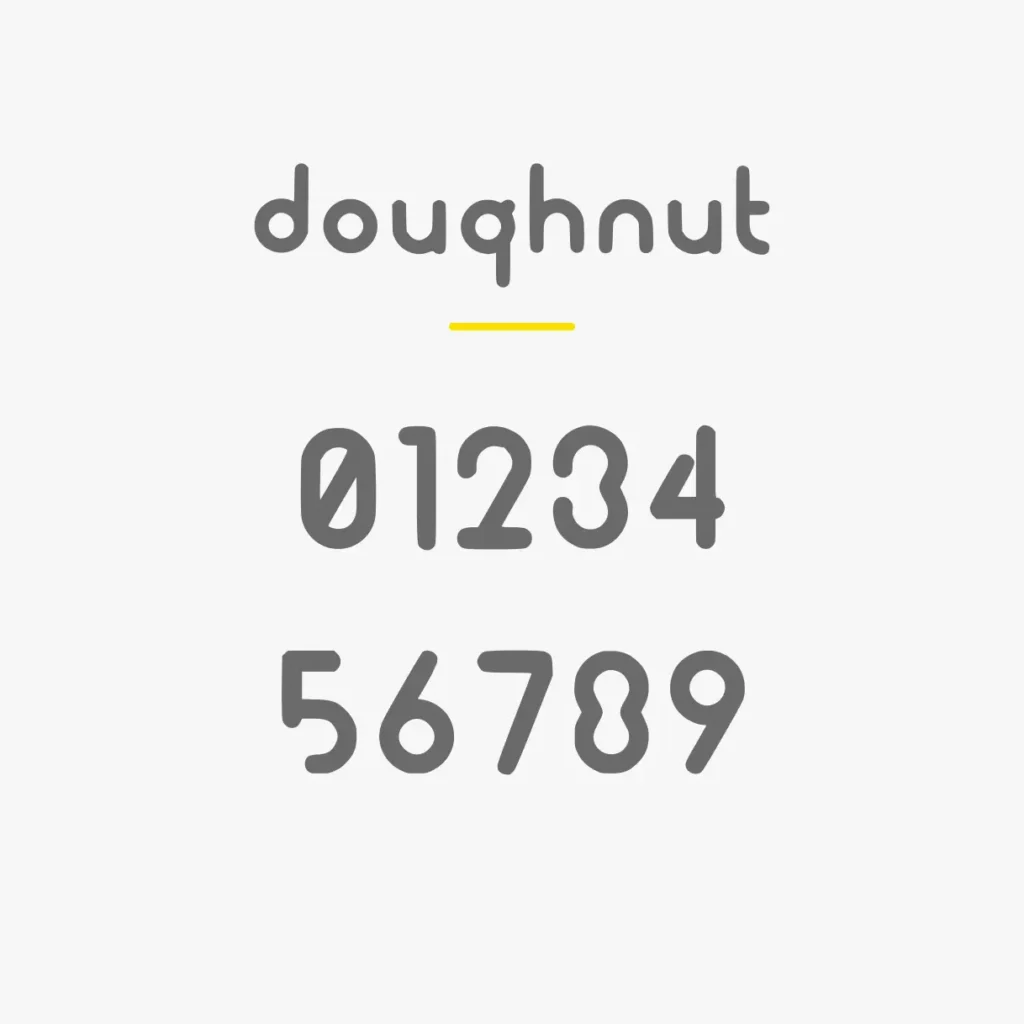
数字フォントは、ロゴやポスター、SNS画像、動画サムネイル、資料制作など幅広いシーンで活躍します。同じ数字でもフォントによって印象は大きく変わり、おしゃれな雰囲気を演出したり、かわいらしさや力強さを表現したりできます。
この記事では、おしゃれ・かわいい・かっこいい・太字で目立つ・レトロ・デジタル風など、用途やデザインテイスト別におすすめの数字フォントを紹介します。無料で使えるフォントや商用利用できるフォントも掲載しているので、数字デザインにこだわりたい方はぜひ参考にしてください。
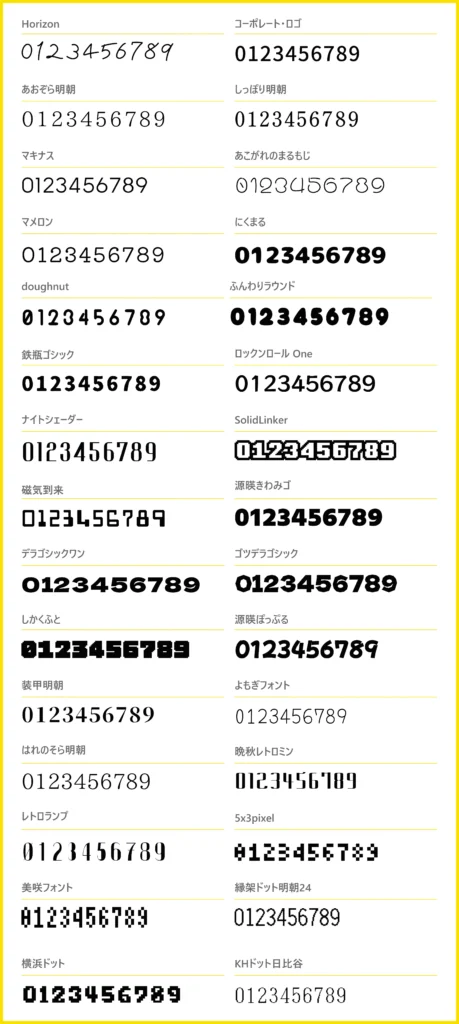
数字フォントを選ぶポイント
数字フォントを選ぶ際は、デザイン性だけでなく視認性や利用用途も重要です。数字は価格表示やランキング、背番号、時計表示など情報を伝える役割が強いため、用途に適したフォントを選ぶことで見やすさや訴求力が向上します。
用途に合わせて数字フォントを選ぶ
数字フォントには、ロゴ向け・ポスター向け・スポーツ向け・デジタル表示向けなどさまざまな種類があります。まずは使用目的を明確にし、デザインとの相性を確認しながら選びましょう。
数字の見やすさを確認する
数字フォントによっては「1」と「7」、「0」と「O」などが似て見える場合があります。資料や価格表など正確な情報伝達が必要な場面では、判別しやすい数字デザインを選ぶことが大切です。
日本語フォントとの相性も重要
数字だけが目立ちすぎると全体のデザインバランスが崩れることがあります。本文や見出しで使用する日本語フォントとの組み合わせも意識すると、統一感のあるデザインに仕上がります。
おしゃれな数字フォントおすすめ
洗練された数字デザインは、ロゴやブランドサイト、価格表示などに適しています。シンプルながらも存在感のある数字フォントを選ぶことで、デザイン全体を上品に見せることができます。
Horizon
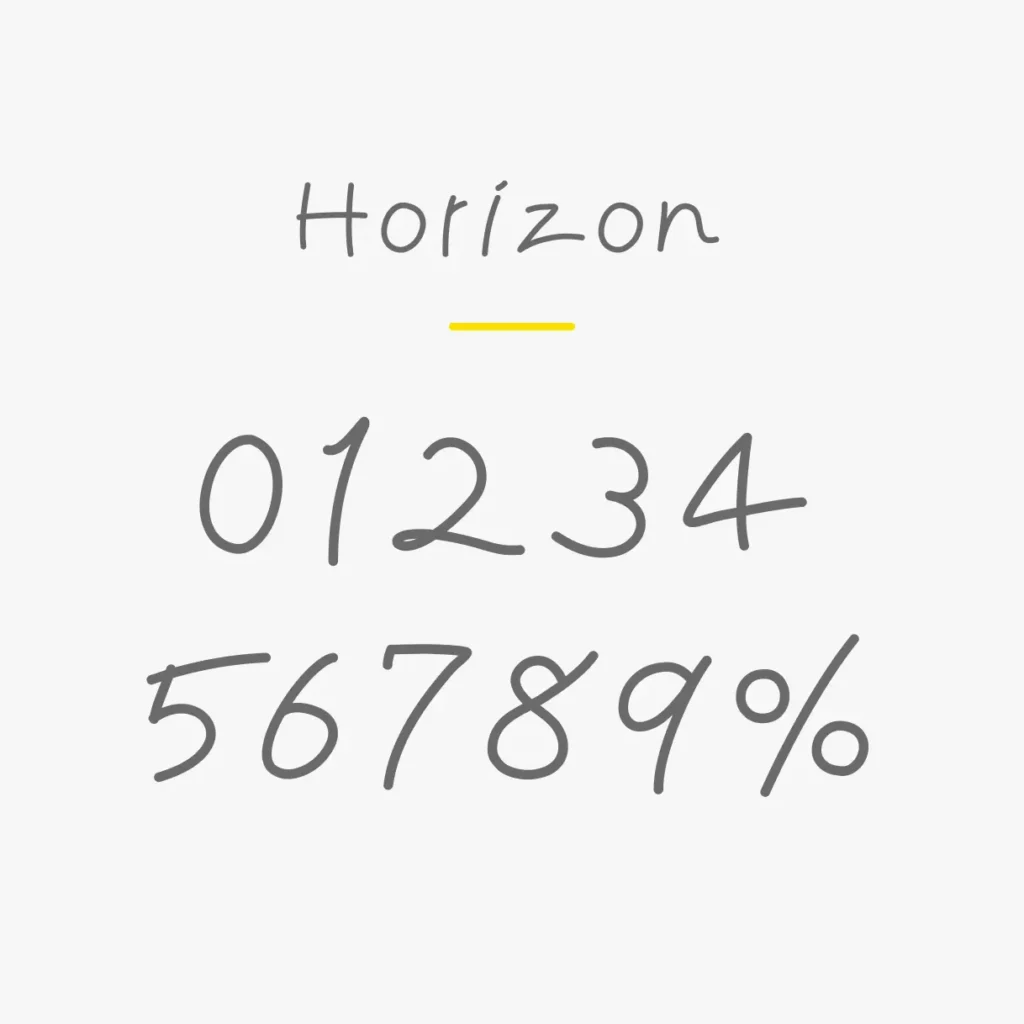
| ジャンル | おしゃれ・近未来 |
| 数字の雰囲気 | シャープ・未来的 |
| おすすめ用途 | ロゴ・サムネイル・ポスター |
| 相性のいいデザイン | テクノロジー・SF・ミニマル |
近未来的でスタイリッシュなデザインが特徴のフォントです。直線的な数字デザインが印象的で、テクノロジー系やファッション系のデザインに向いています。
コーポレート・ロゴ
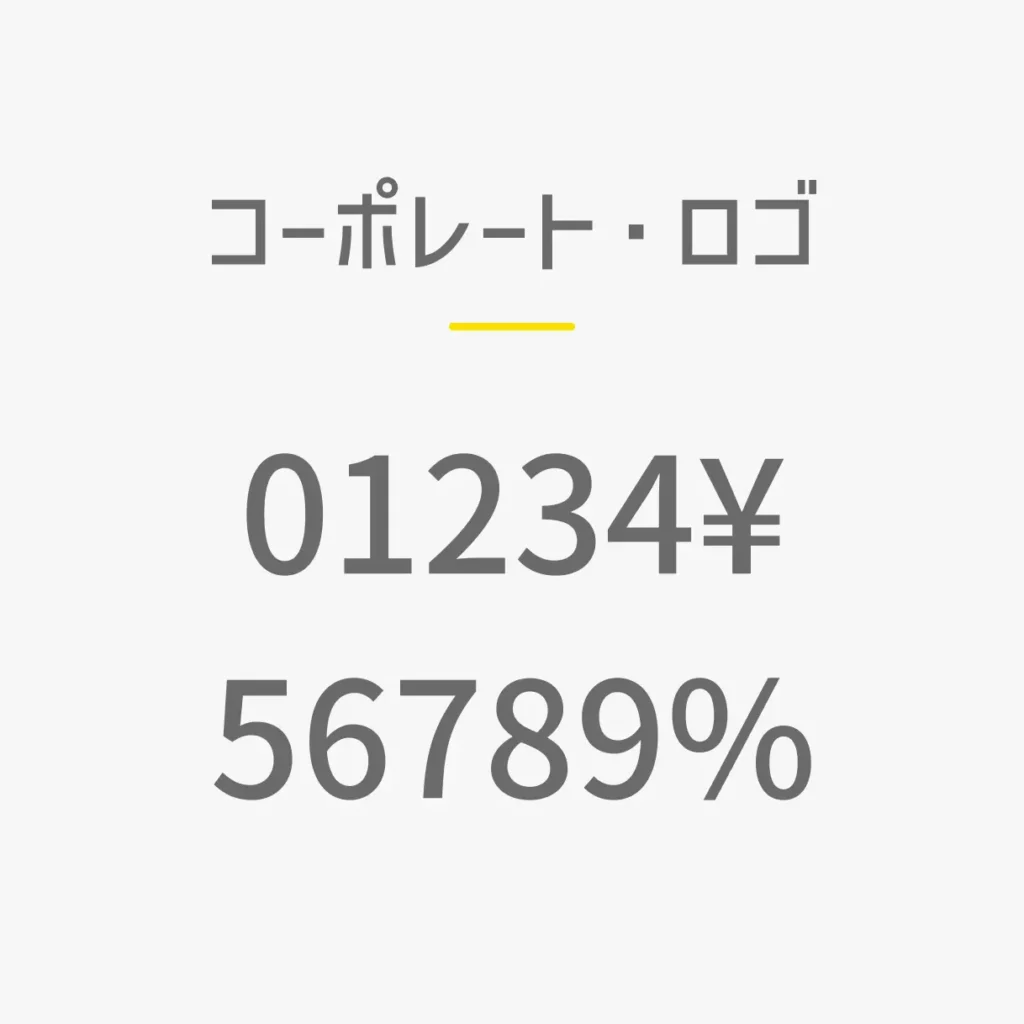
| ジャンル | シンプル・モダン |
| 数字の雰囲気 | すっきり・読みやすい |
| 相性のいいデザイン | ミニマル・コーポレート |
視認性とデザイン性を兼ね備えた人気フォントです。数字も美しく整っており、ロゴ制作やWebデザイン、資料作成など幅広い用途で活用できます。
あおぞら明朝
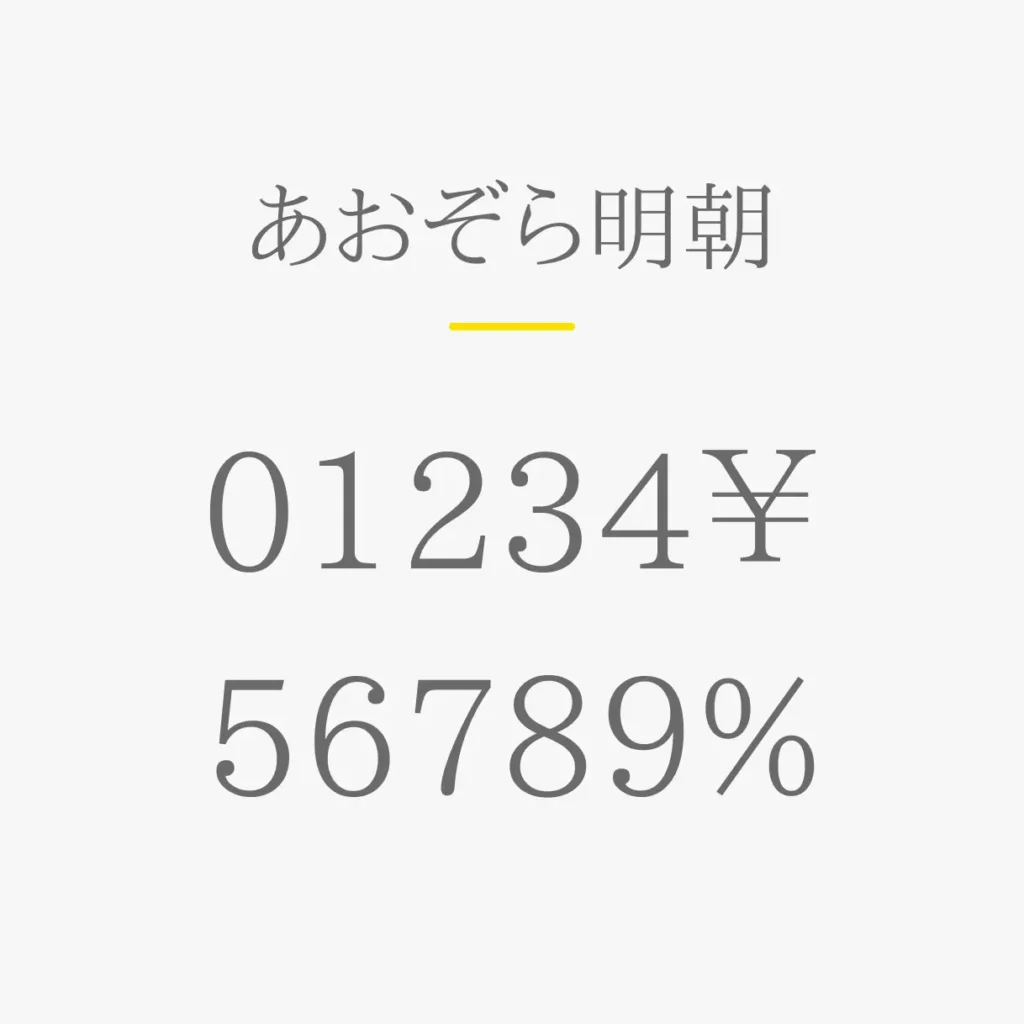
| ジャンル | おしゃれ・明朝体 |
| 数字の雰囲気 | 上品・繊細 |
| 相性のいいデザイン | 和モダン・ナチュラル |
上品で落ち着いた雰囲気を持つ明朝体フォントです。数字にも繊細な印象があり、高級感のあるデザインや和モダンな表現に適しています。
しっぽり明朝
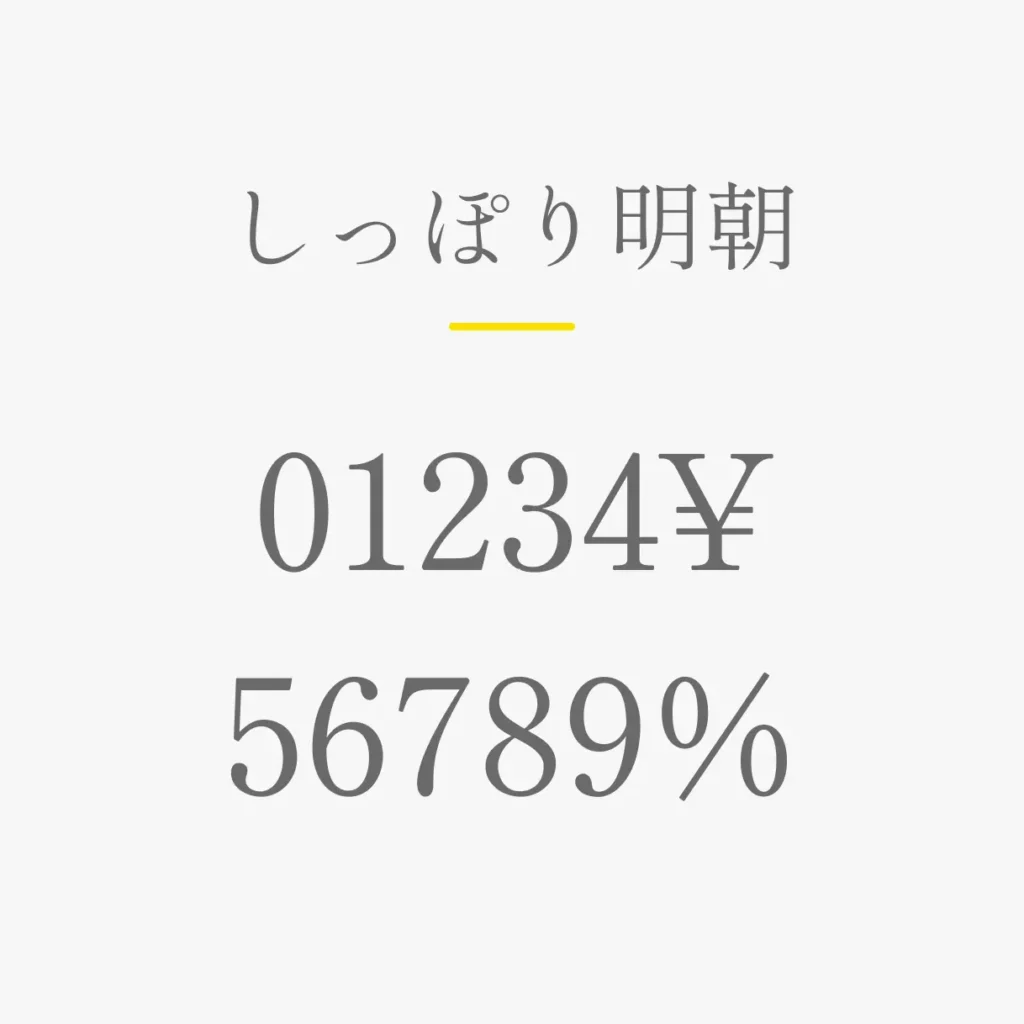
| ジャンル | 和モダン |
| 数字の雰囲気 | 上品・やわらかい |
| 相性のいいデザイン | 韓国風・和モダン |
和モダンな雰囲気を持つ明朝体フォントです。数字にも品のある印象があり、美容系やブライダル関連のデザインにも人気があります。
マキナス
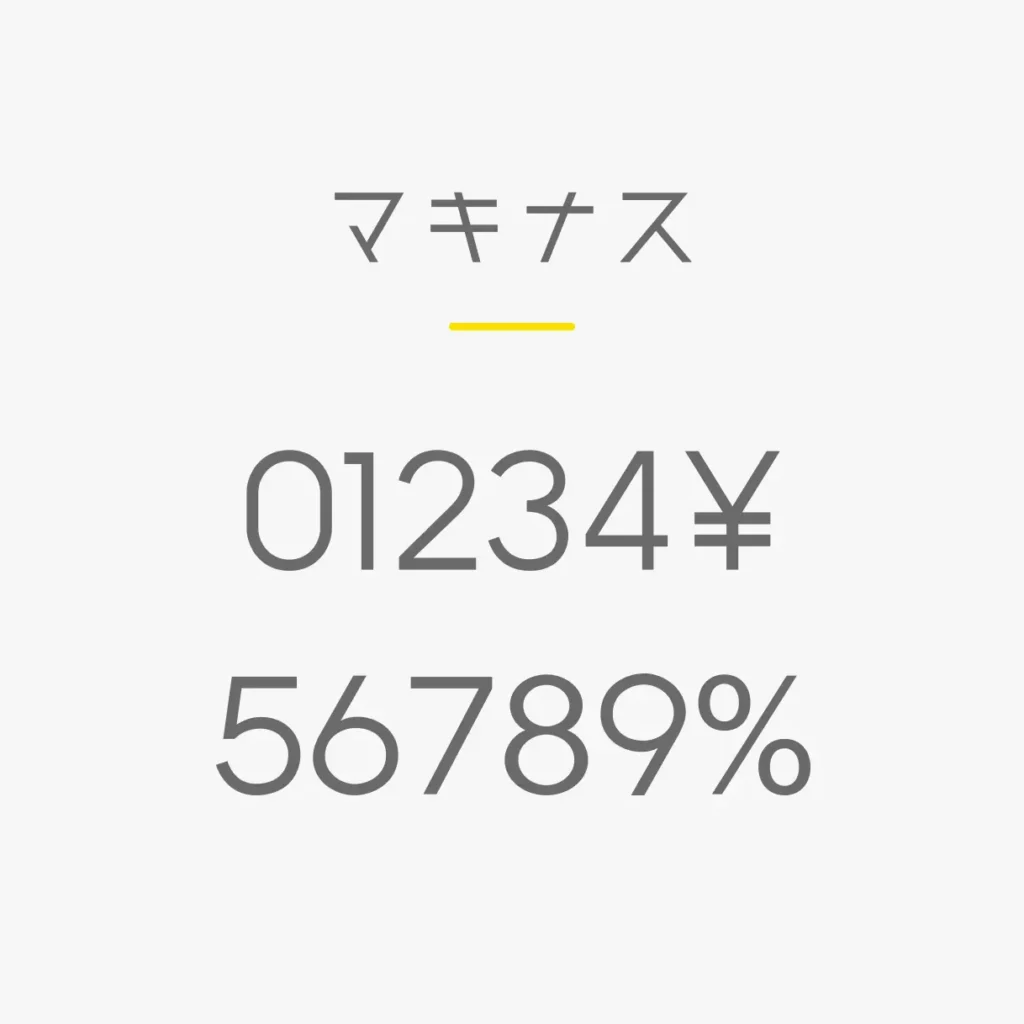
| ジャンル | レトロ・デザイン系 |
| 数字の雰囲気 | 個性的・レトロ |
| 相性のいいデザイン | ヴィンテージ・昭和レトロ |
レトロ感とデザイン性を兼ね備えた人気フォントです。数字にも独特の味わいがあり、ポスターやロゴ制作など幅広いデザインに活用できます。
かわいい数字フォントおすすめ
柔らかく親しみやすい数字フォントは、SNS投稿や子ども向けデザイン、イベント告知などにおすすめです。
あこがれのまるもじ
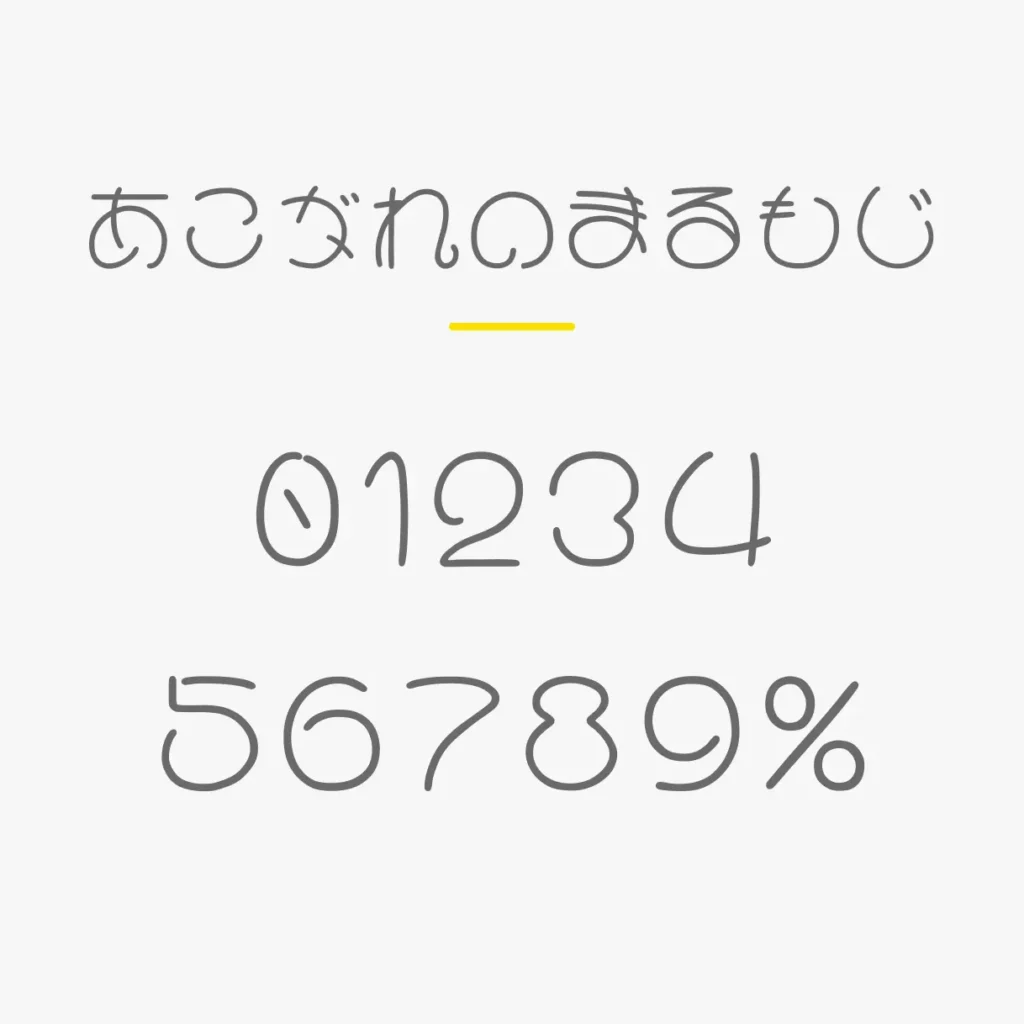
| ジャンル | かわいい・丸文字 |
| 数字の雰囲気 | やさしい・ふんわり |
| 相性のいいデザイン | ナチュラル・ガーリー |
丸みのある数字デザインが特徴のフォントです。優しくかわいらしい印象があり、SNS投稿やイベント告知などにもおすすめです。
マメロン
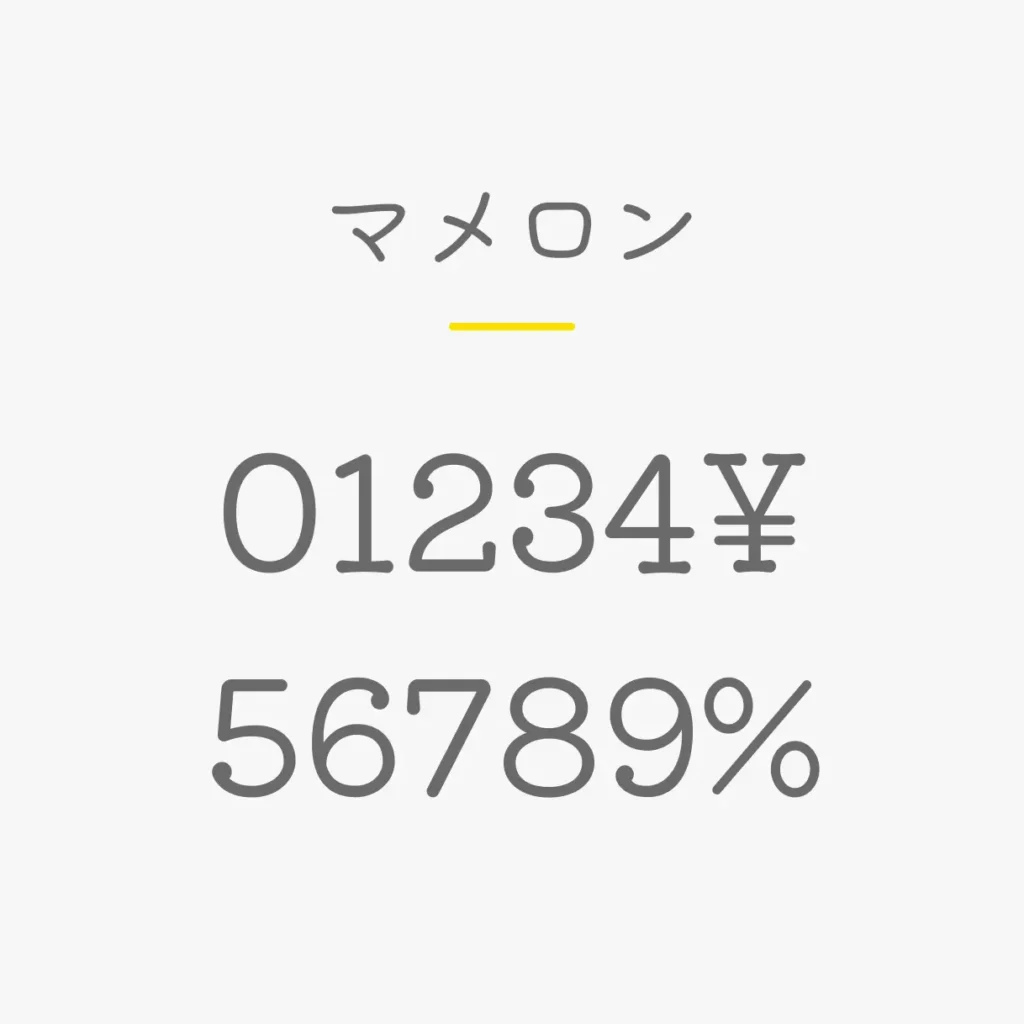
| ジャンル | かわいい・ポップ |
| 数字の雰囲気 | 丸み・ポップ |
| 相性のいいデザイン | ポップ・子ども向け |
ポップで親しみやすいデザインが魅力のフォントです。数字も丸みが強く、楽しく明るい雰囲気を演出したい場面に向いています。
にくまる